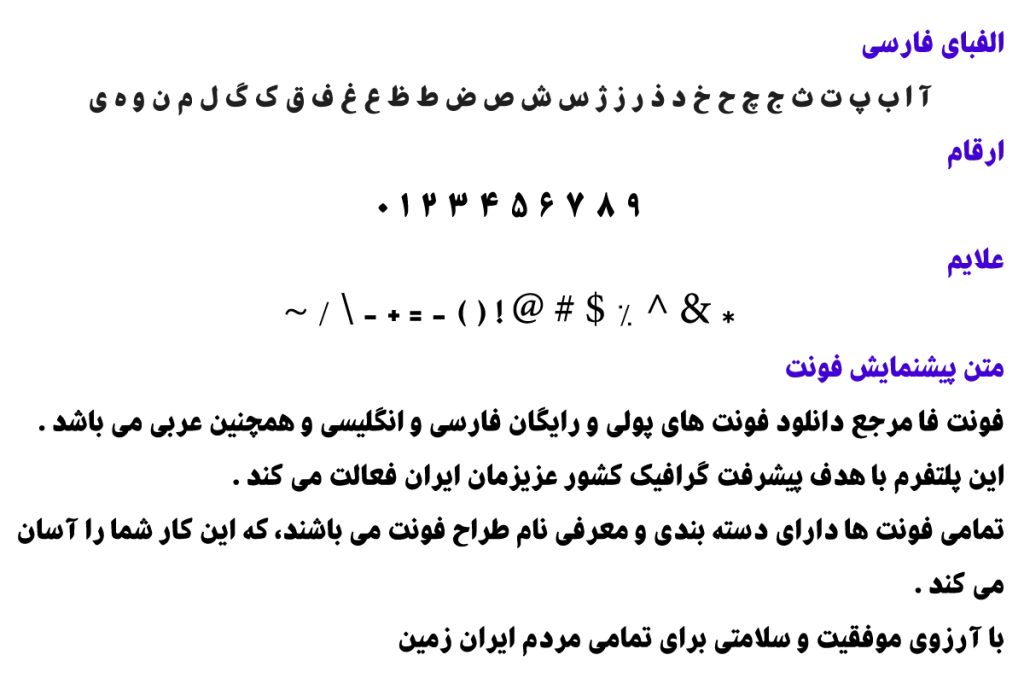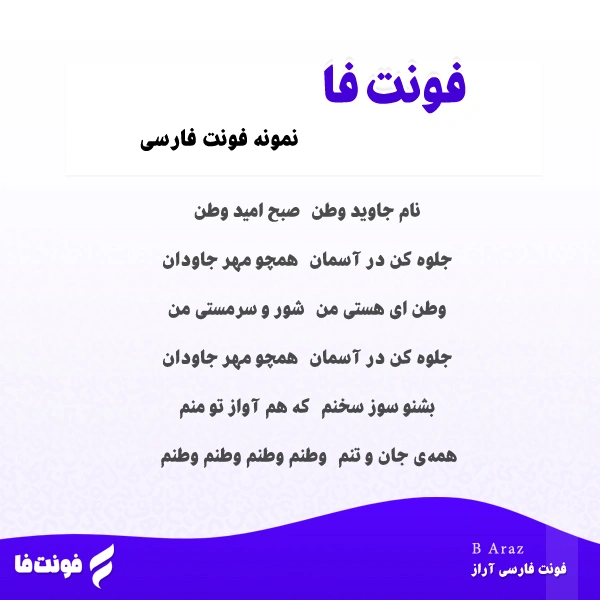
فونت فارسی آراز – B Araz
سال ساخت فونت: 1391
مجموعه فونت: فونت سری B
طراح فونت: محمدرضا شمس الکتابی نوع فونت: فونت عنوان
پیشنمایش فونت بی آراز
توضیحات و معرفی فونت آراز
فونت فارسی آراز ( B Araz ) از مجموعه فونت های سری B می باشد، و نیز نوع فونت عنوان می باشد.
فونت خوشگل مربوط توسط محمدرضا شمس الکتابی در سال 1391 طراحی و ساخته شده است.
و نیز فونت B Araz در یک وزن پر رنگ است.
- B Araz Bold
در تصویر زیر، شعر کهن «وطنم» با این تایپفیس به نمایش گذاشته شده است.